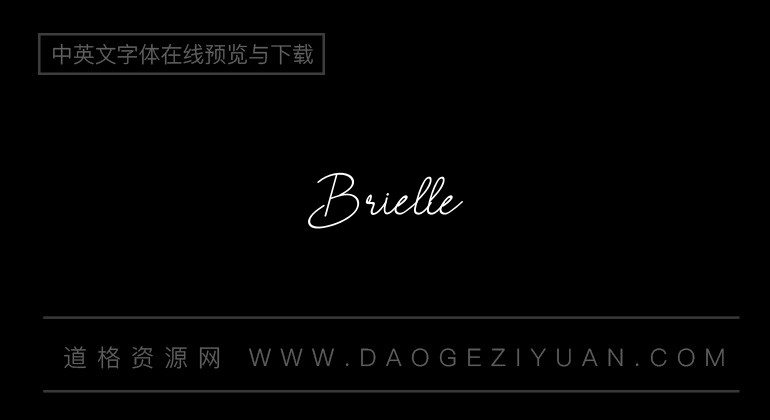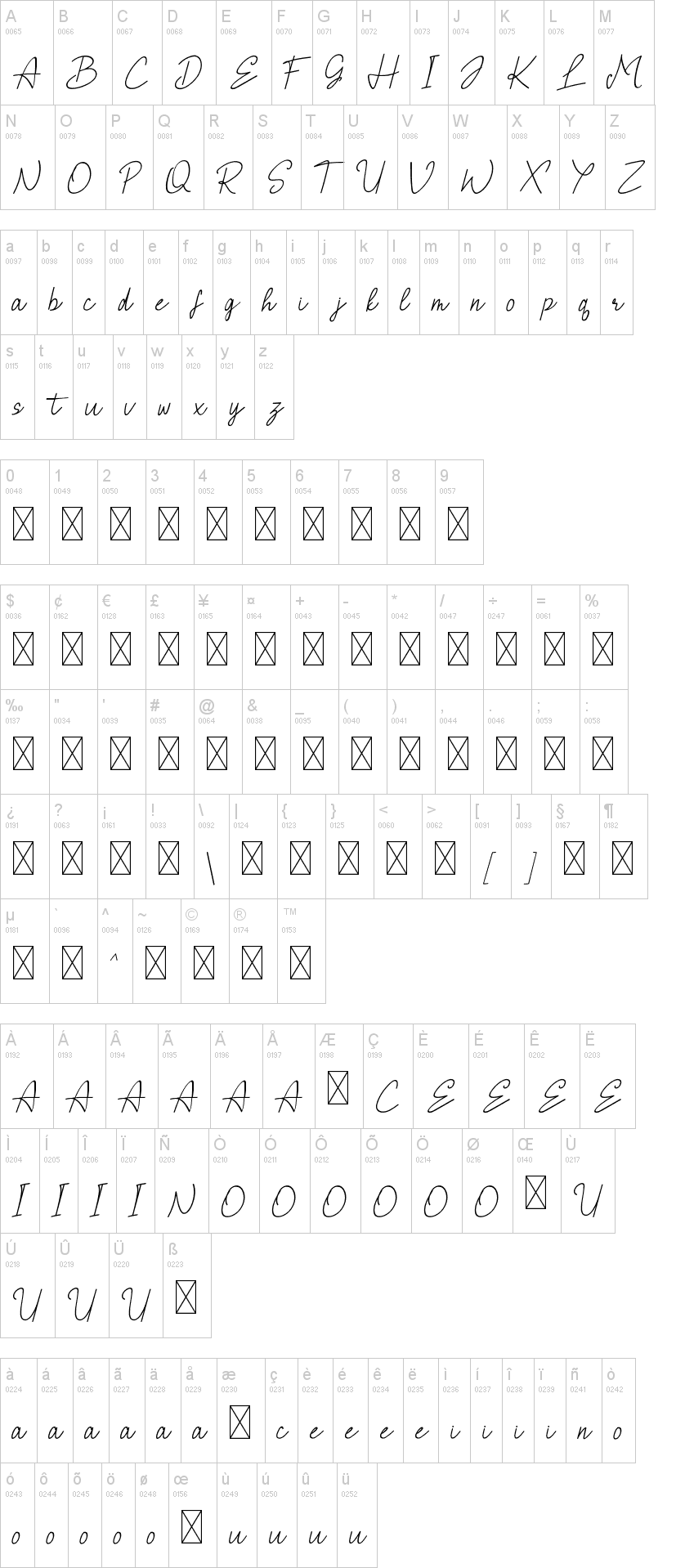
Brielle
Brielle 字体是一款非常优雅的脚本字体,它具有流畅的笔画和舒缓的曲线,能够给文字带来柔和的外观。Brielle 字体的字母可以按照任何顺序排列,它们的连接点也很灵活,可以自由控制,从而使文字看起来更加流畅。Brielle 字体的字形非常完美,适合用于各种印刷品、海报、海报、卡片等。
Brielle是一款非常不错的手写艺术字体,具有很好的视觉感,适合于文化类的宣传设计、商业类品牌的广告和产品包装设计以及个性化文字排版等较多场景。